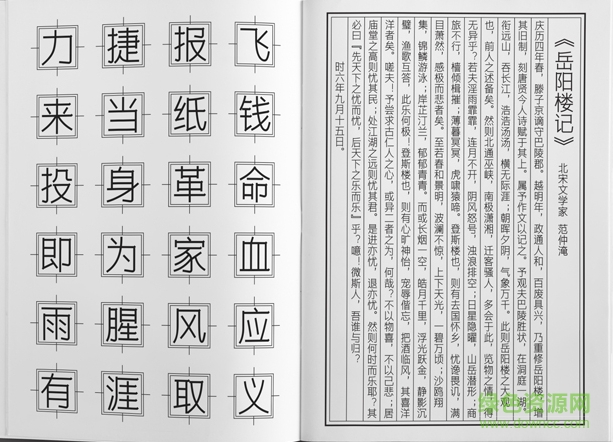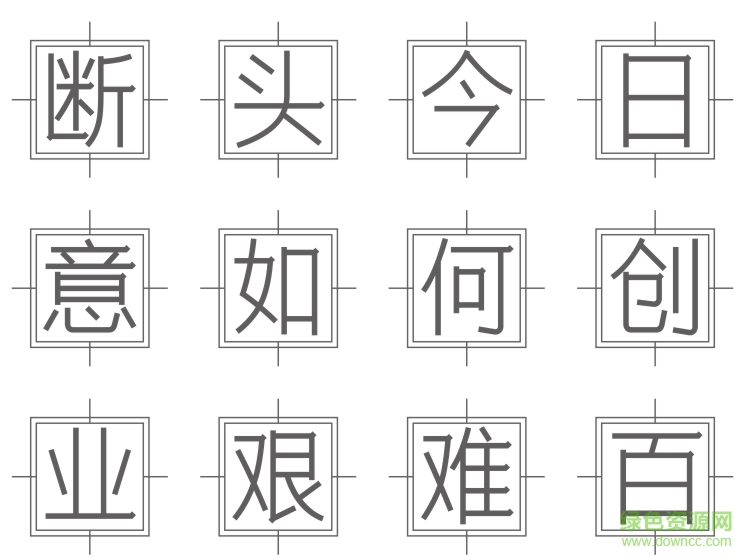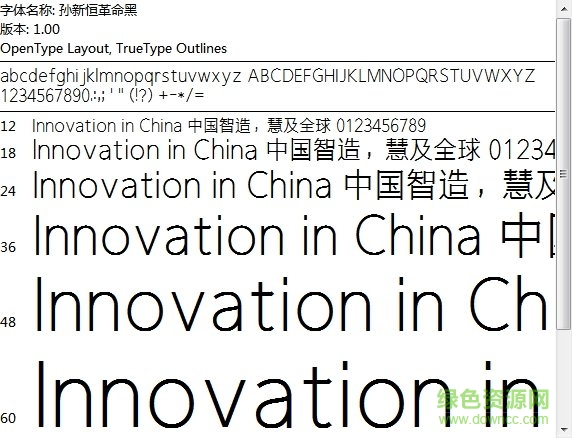
孫新恒革命黑
孫新恒革命黑體是當代設計工作者制作的一款常規(guī)字體,字跡端正大方,行文流暢秀美,很有印刷之風,別具現(xiàn)代美感,喜歡的朋友歡迎在綠色字資源網(wǎng)下載體驗!
孫新恒革命黑字體介紹
孫新恒革命黑,本款字體斷斷續(xù)續(xù)歷時2年才終于出世,共收錄了6763個漢字字符,52個英文字符,10個數(shù)字字符,及其它常用符號。
孫新恒革命黑常規(guī)